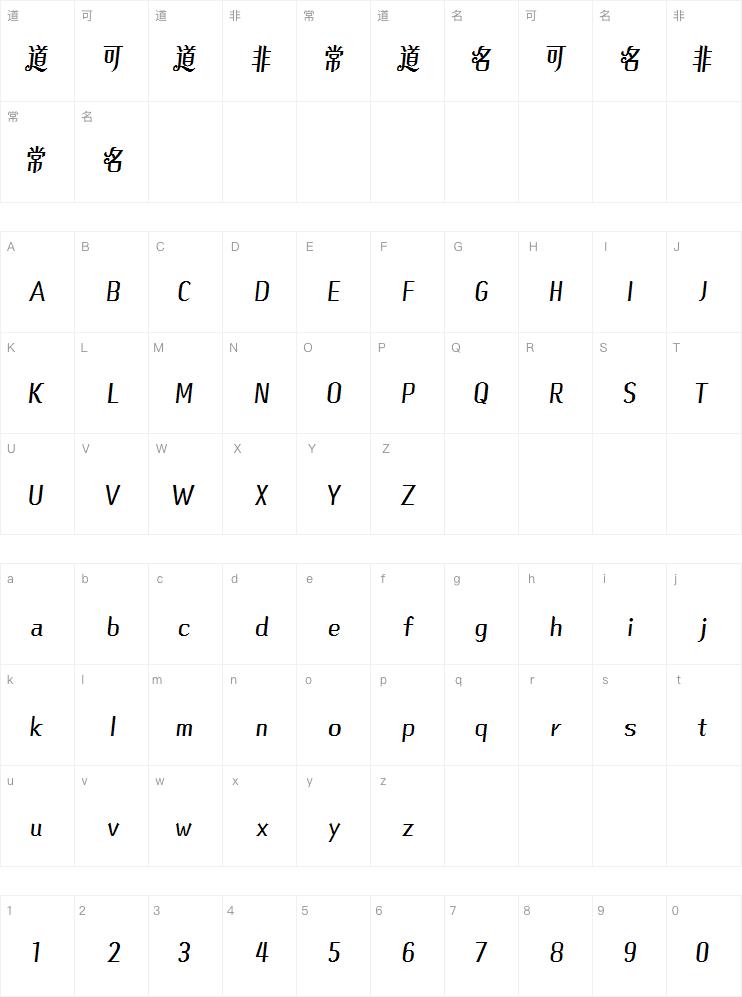
山海圆舞曲 摩登版,是一款全新的字体,包含汉字9169个,符号200+个。该字体是一款花式字体,该字体融合了花式、波浪元素,字体独特,新颖华丽。这款字体有着很强的装饰性和醒目的视觉效果,字体重心略微偏上、结构空间均衡、字面趋于瘦高长方形,字形比例按照宽高4:5的比例设计。最重要的是整体字形上方有6度的向右倾斜,从而增加整体字体的灵动性,给予视觉上最直接的动态感。字形灵动多变,童趣可爱,同时融入花型笔画造型,装饰性十足,带给人华丽的视觉感受。撇和捺作为字形中延展性最高的两个笔画,形态华丽灵动。整体笔触造型生动有趣,具有灵活的适用性,天真俏皮又不失时尚感。在体现欧式风格的同时呼应了中文的笔画特征,并在设计上有意改善传统花式字体复杂难辨认的特性,尽量做到易辩、易读,保证了字体的实用性。汉字艺术与西方元素的融合,如在维也纳音乐殿堂里奏响的华丽高贵的圆舞曲,又宛如巴黎圣母院里响起的梦幻华尔兹;个性鲜明的字体特征,散发着神秘而华丽的气息。在华丽而不失婉约中,感受圆舞曲般文字的魅力。